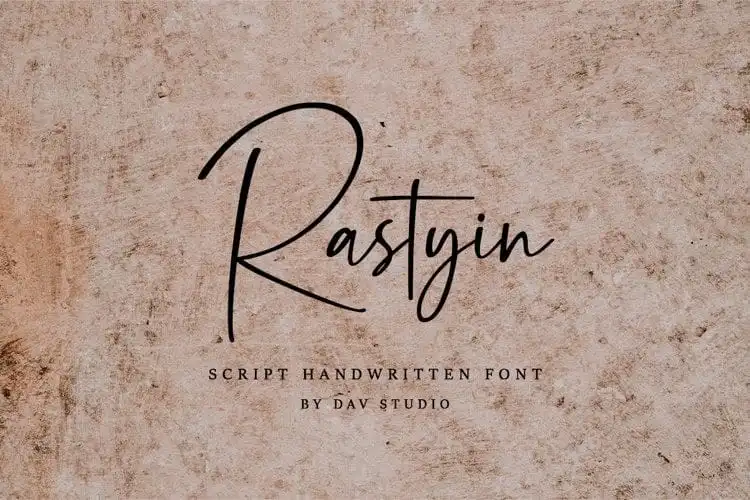
Rastyin Handwritten Font – Download Grátis
A fonte Rastyin Handwritten é uma obra prima que transmite a essência da autenticidade através do seu estilo de escrita manual cuidadosamente desenhado. Com um design natural e suave, este fontes script oferece o ideal para diversas aplicações, desde os logotipos até as cartas de convidado, passando por etiquetas de nome, frases escritas a mão e embalagens de produtos, entre outros usos criativos. Com um amplo conjunto de letras maiúsculas e minúsculas, uma grande variedade de pontuação, símbolos numéricos, bem como suporte multilíngue, esta fonte é perfeita para criar mensagens memoráveis. O design em mão livre traz à tona o aspecto autêntico que tanto busca a sua identidade visual, tornando-a uma opção excepcional tanto para iniciantes quanto para profissionais dedicados ao mundo do design gráfico. Este Rastyin Handwritten é um recurso valioso e encorajador, fornecendo aos criativos uma maneira fantástica de traduzir a personalidade única de seus projetos em algo visualmente emocionante. Com seu estilo elegante e orgânico, esta fonte atinge a perfeição entre a modernidade e o vintage, tornando-se um elemento indispensável no arsenal de qualquer designer gráfico.